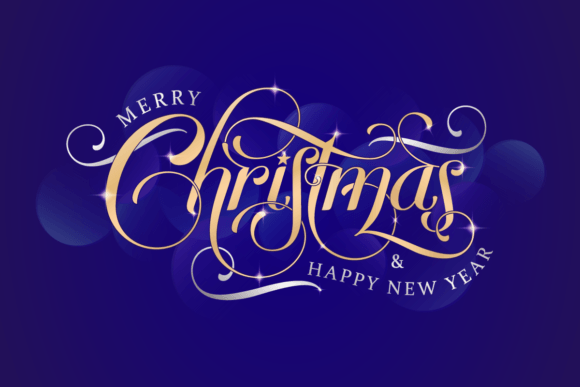
Merry Christmas Lettering Fonts
Mencari elemen reka bentuk yang sesuai boleh menjadi mencabar, tetapi Merry Christmas Lettering Fonts menawarkan koleksi luar biasa yang menaik taraf karya anda serta-merta.
Dicipta dengan ketepatan, Merry Christmas Lettering Fonts menyediakan vektor yang bersih, tipografi yang licin dan lesen komersial untuk ketenangan fikiran.
Sama ada anda mencipta produk POD (Print on Demand), jemputan perkahwinan atau grafik media sosial, Merry Christmas Lettering Fonts amat bersesuaian.